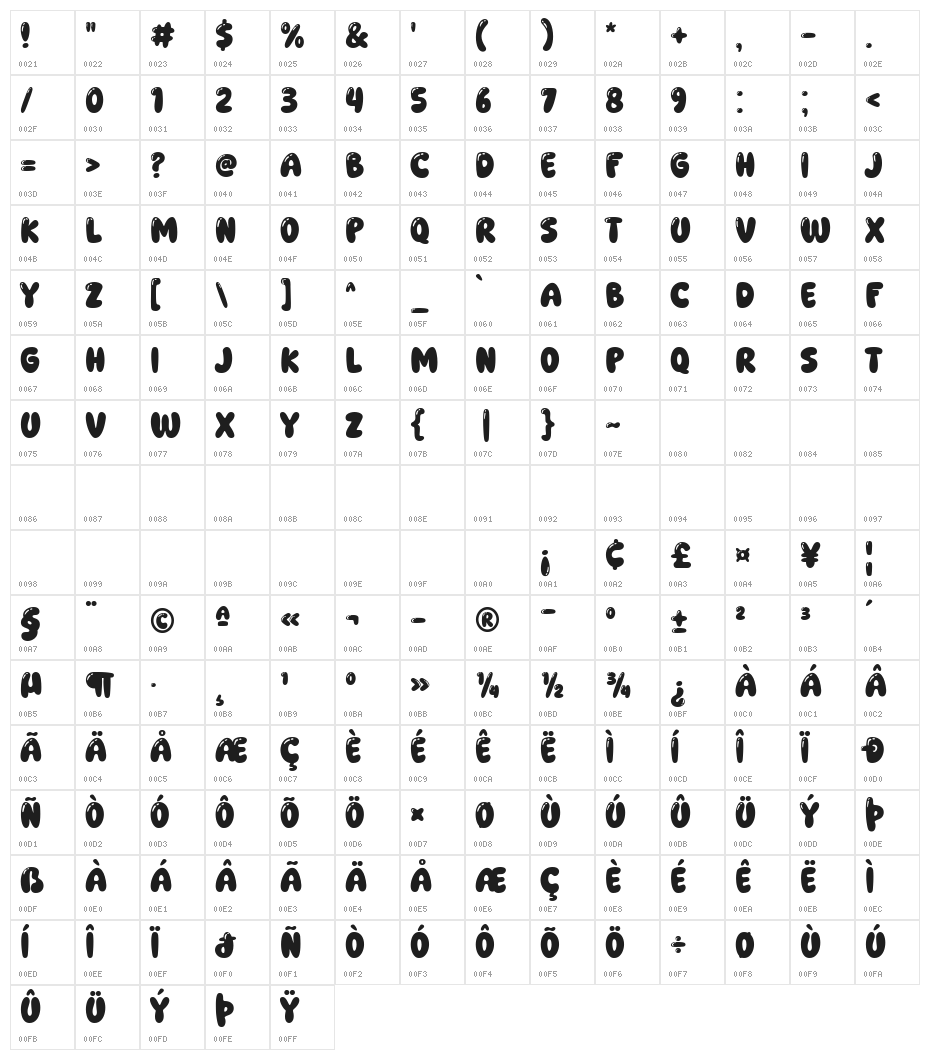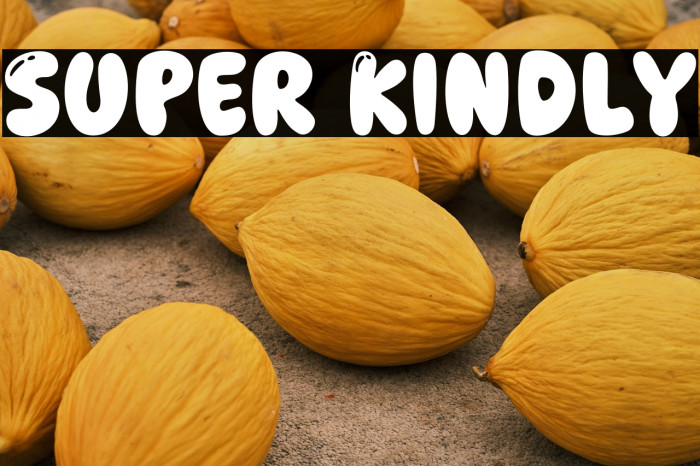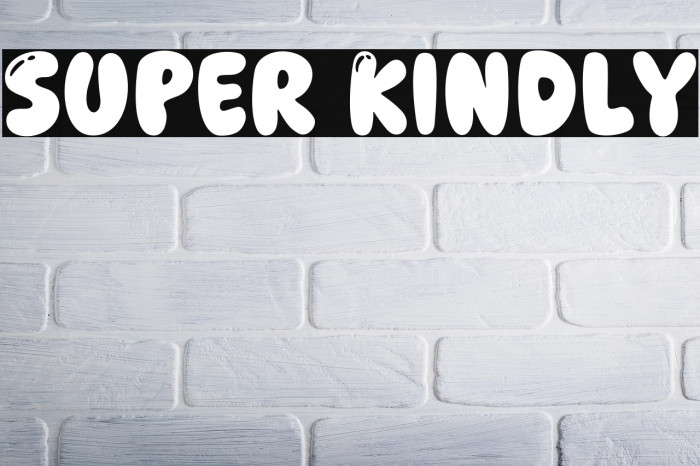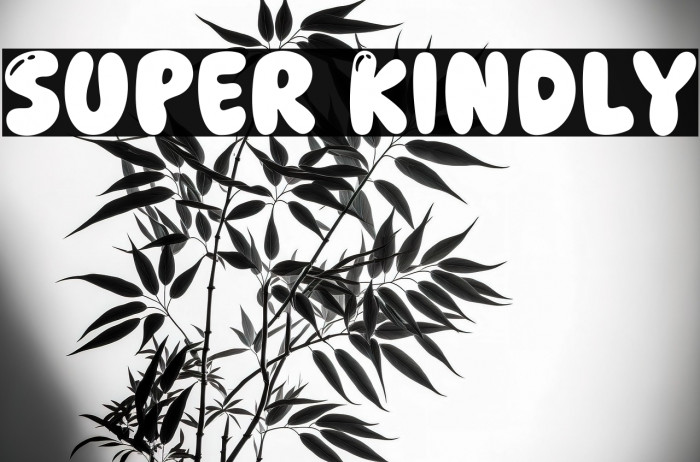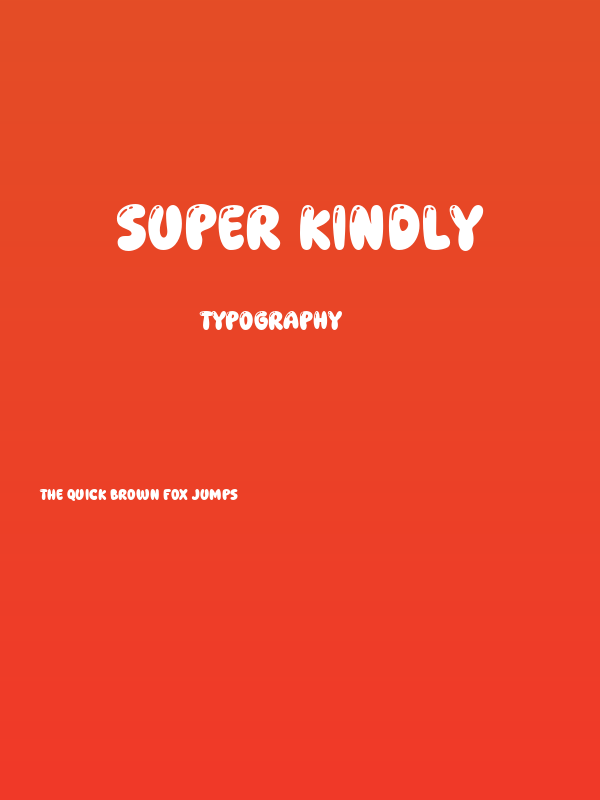
Super Kindly Font
| Stile generale | Playful, Whimsical |
| Progetti proposti | Ideal for children's books, party invitations, playful branding, and any project needing a fun, lighthearted touch. |